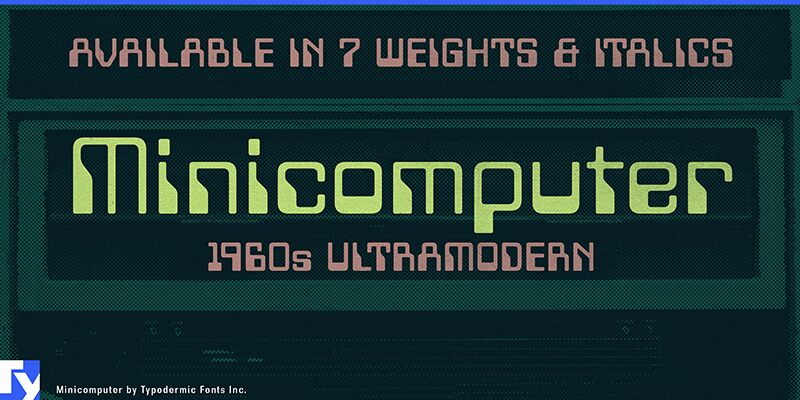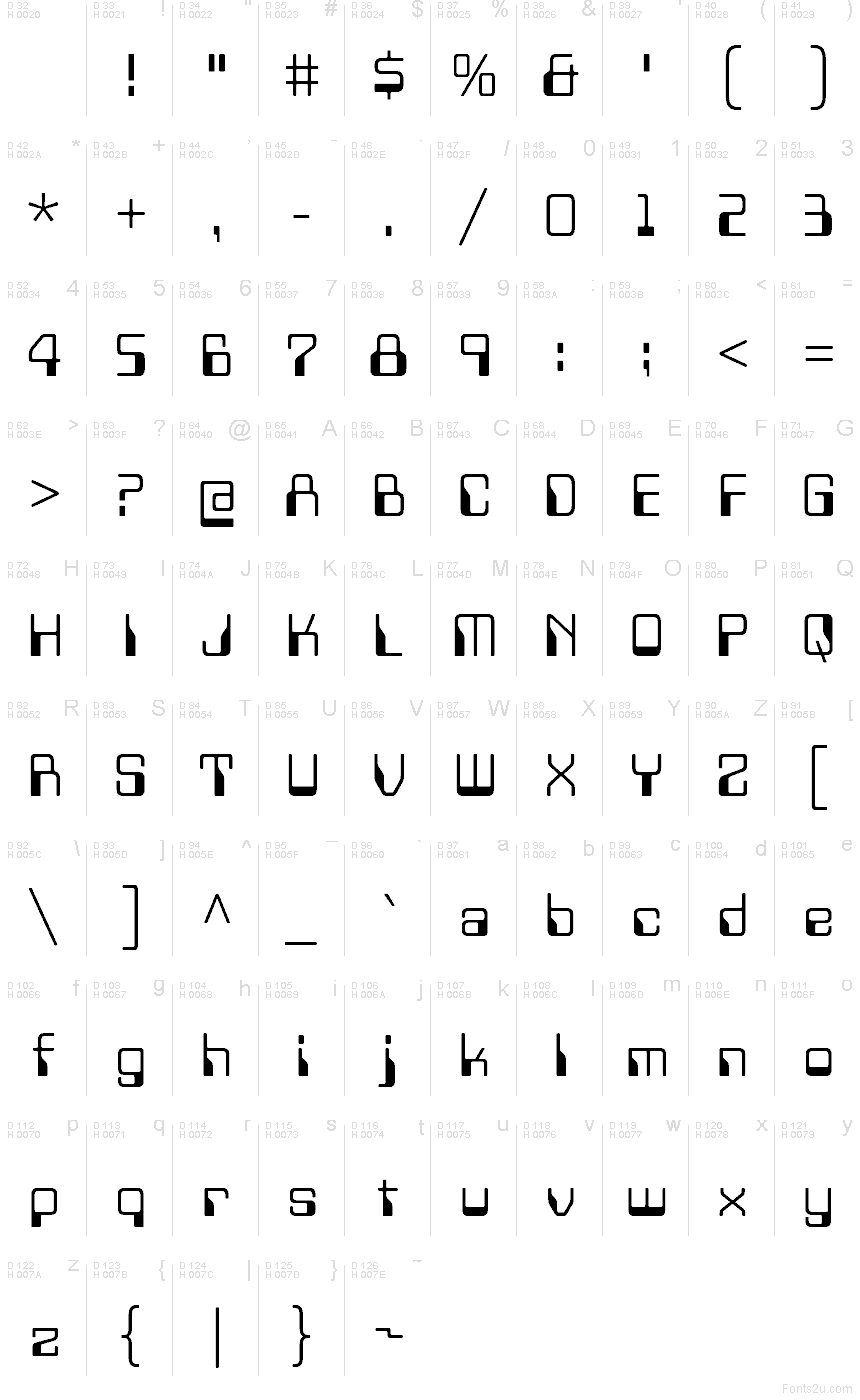
Minicomputer es una tipografía para titulares (display) inspirada en los caracteres MICR E-13B que solían imprimirse en los cheques bancarios. Combina la precisión informática de mediados del siglo XX con el espíritu lúdico del retrofuturismo de los años sesenta, transformando un estilo estrictamente funcional en algo expresivo y con estilo.
Sus formas cuadradas y las figuras distintivas de sus números evocan las lecturas de las máquinas antiguas, mientras que un alfabeto completo amplía su uso a titulares, identidad de marca, carteles y diseño editorial. Gracias a su amplia compatibilidad de idiomas y a un ritmo geométrico nítido, Minicomputer aporta un toque retro-tecnológico a la tipografía moderna.